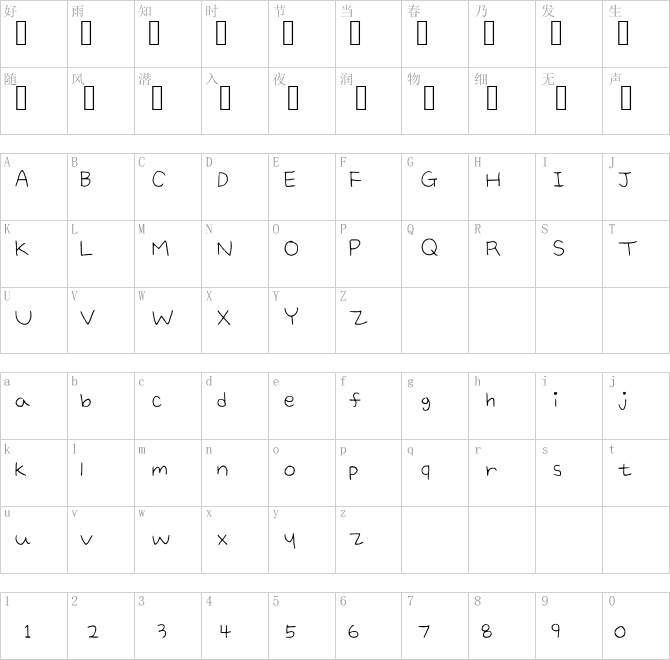
나눔손글씨 반짝반짝 별韩国字体
나눔손글씨 반짝반짝 별韩国字体,这款字体结构工整、笔画清晰,兼顾美观与易读性,适用于标题、正文、海报、包装、LOGO 等多种场景。字形优雅稳定,风格百搭耐看,适配日常排版与创意设计,让文字呈现更舒适、更具质感。나눔손글씨 반짝반짝 별韩国字体一笔一画,皆是细节,以均衡的比例、流畅的线条打造舒适视觉体验,字形端正大气,风格简约现代。无论是商业设计、品牌宣传还是日常排版,都能轻松驾驭,让文字更有格调与力量。나눔손글씨 반짝반짝 별韩国字体字体下载。
• 字体名称:나눔손글씨 반짝반짝 별
• 字体风格:Regular
• 字体标识:CLOVA OCR : Nanum BanJjagBanJjagByeor
• 字体全称:나눔손글씨 반짝반짝 별
• PostScript:NanumBanJjagBanJjagByeor